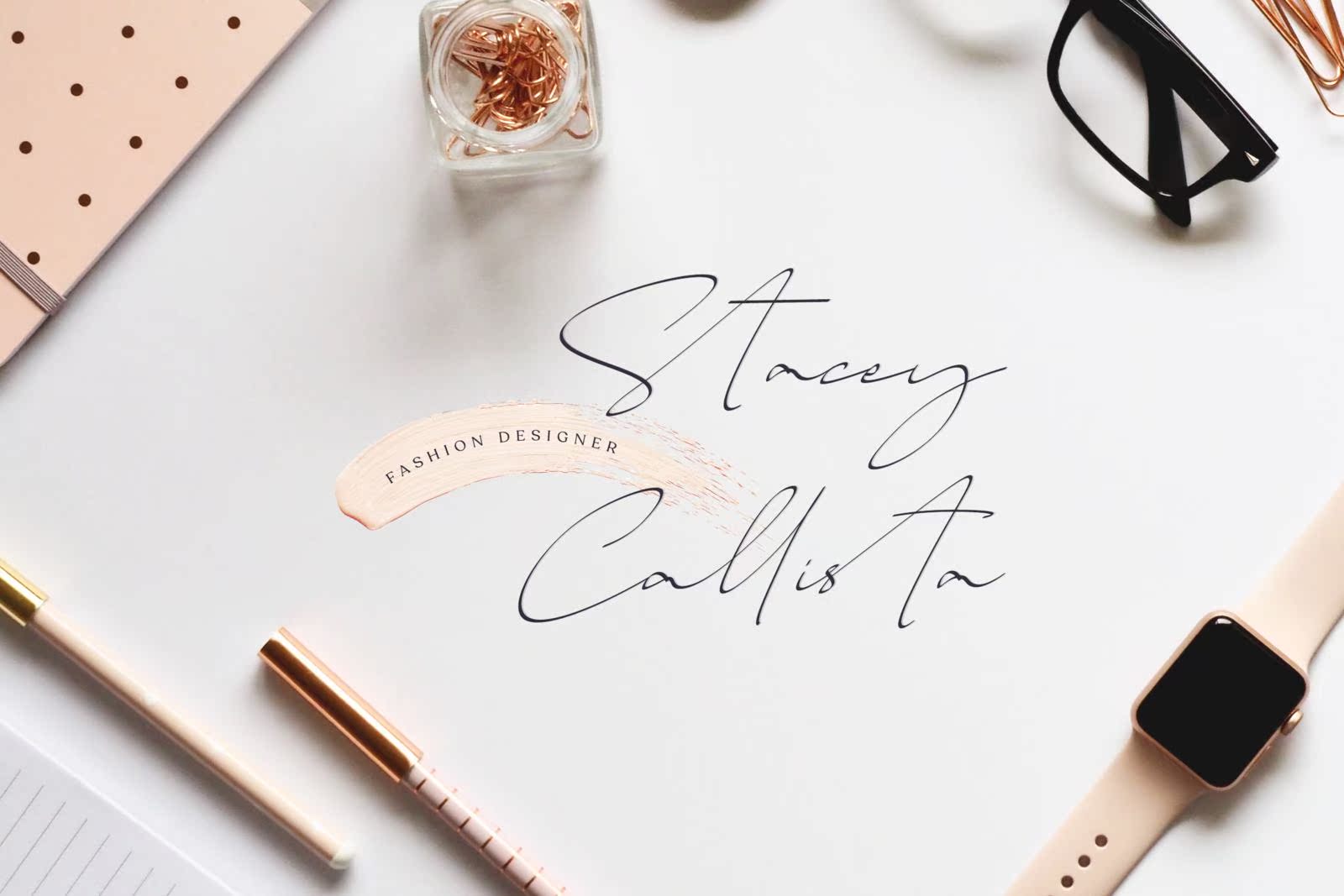
CalliGraScriptAnatural和WrittenFont,完美适用于徽标、邀请函、文具、婚礼设计、社交媒体、广告、产品包装、产品设计、标签、照片水印、特价商品或任何东西。CalliGracome包括全套大写和小写字母、小写字母、多语言支持,数字和标点符号。CalliGraScriptAnatural和WrittenFont,完美适用于徽标、邀请函、文具、婚礼设计、社交媒体、广告、产品包装、产品设计、标签、照片水印、特价商品或任何东西。CalliGracome全套大写和小写字母、小写字母、多语言支持,数字和标点符号。